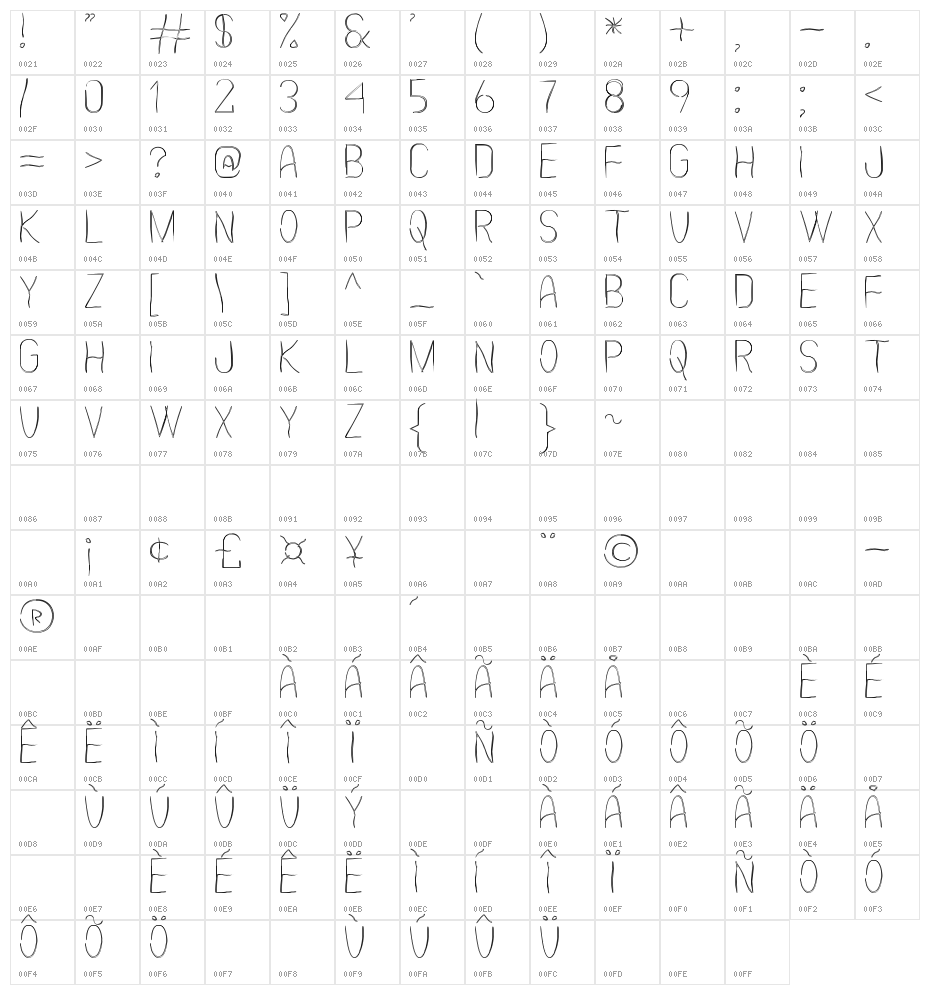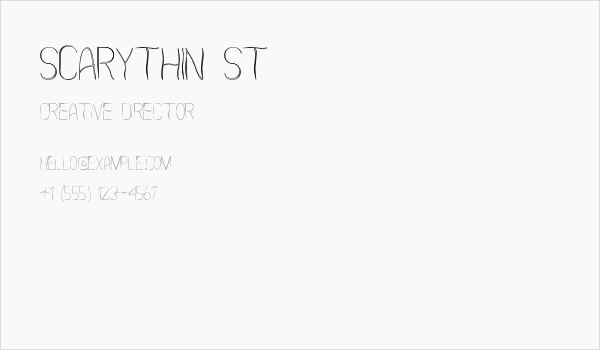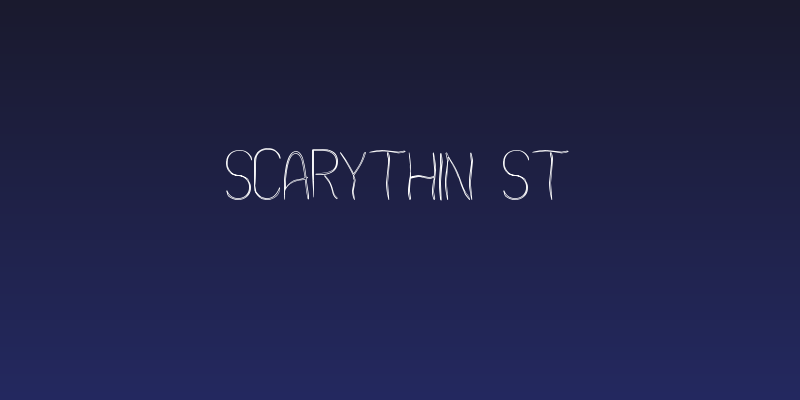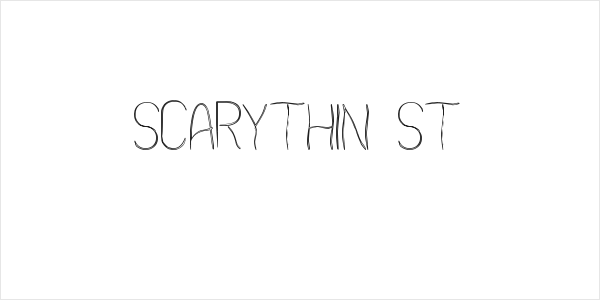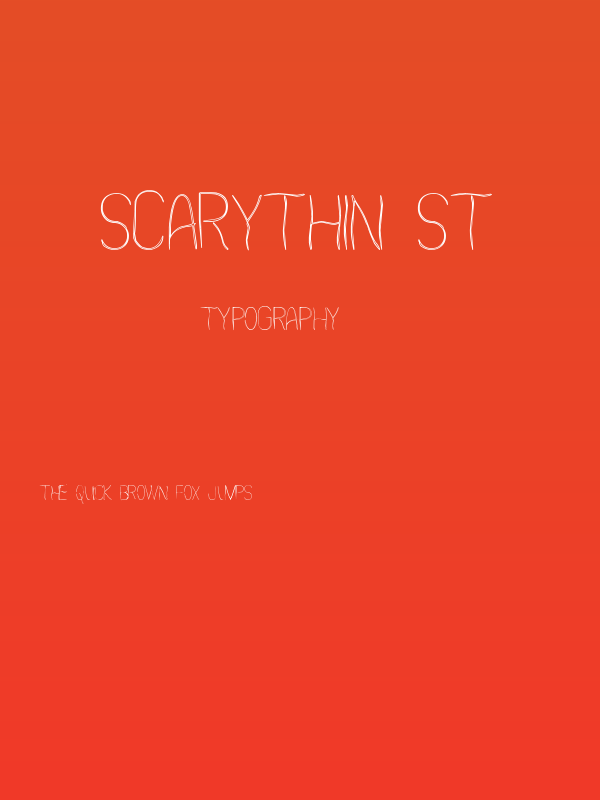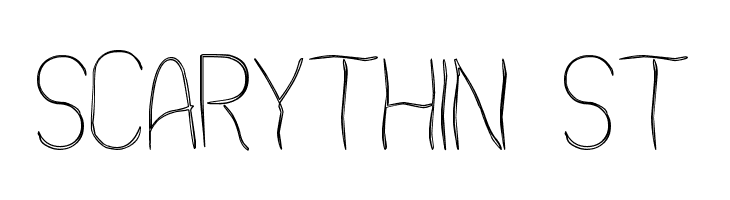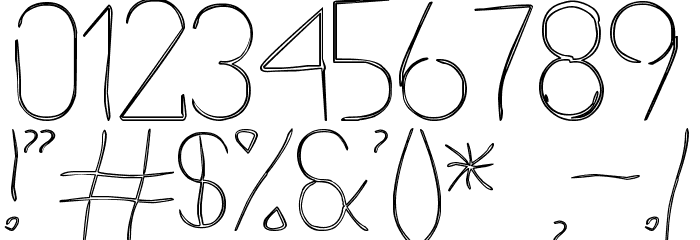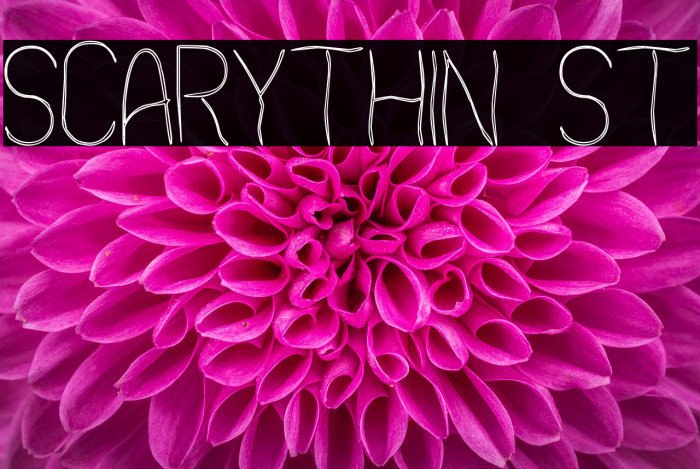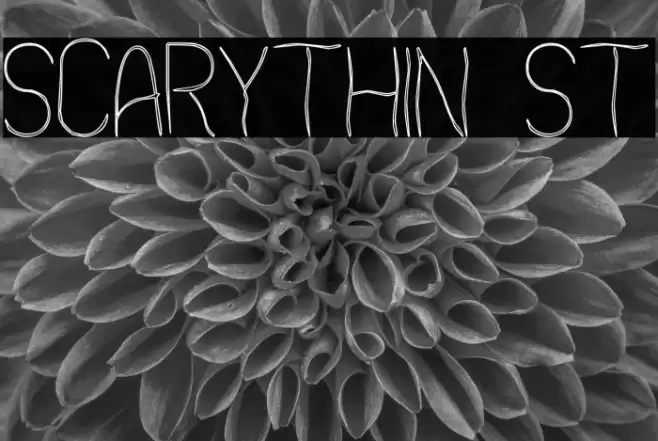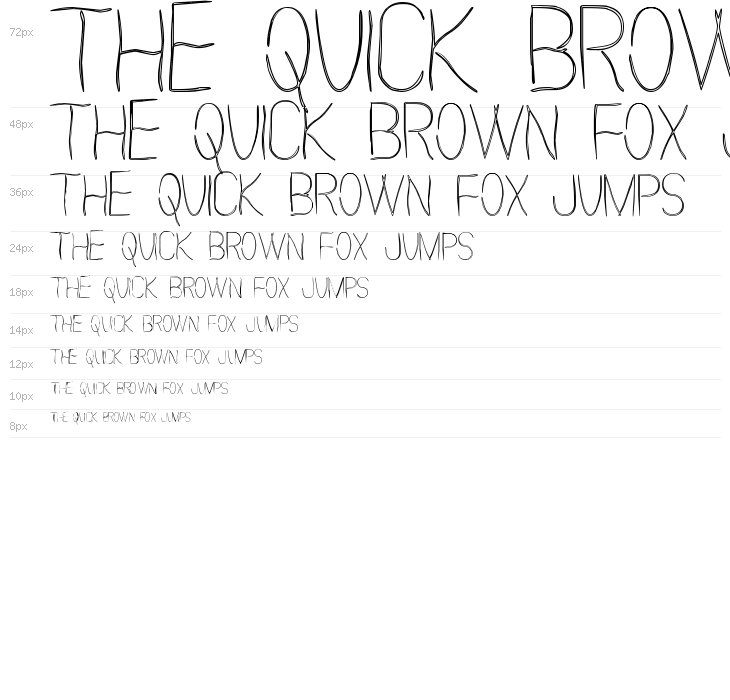
Scarythin St Font
✎ Handwritten
| श्रेणियाँ | Handwritten |
| चौड़ाई | Condensed |
| समग्र शैली | Decorative |
| उपयोग का मामला | Headlines, Logos, Creative projects |
| सुझाए गए प्रोजेक्ट | Ideal for Halloween-themed designs, creative posters, children's book illustrations, and artistic branding projects. |